第294回企画展
「秀英体100」
2011年、ギンザ・グラフィック・ギャラリー
新年最初の企画展は「秀英体100」と題し、秀英体の展覧会を開催いたしました。
オープニングは大賑わい!
このあと「秀英体100」は大阪(3/22~5/11、dddギャラリー)、福島(6/11~9/11、CCGA現代グラフィックアートセンター)へと巡回いたします。どうぞお楽しみに!
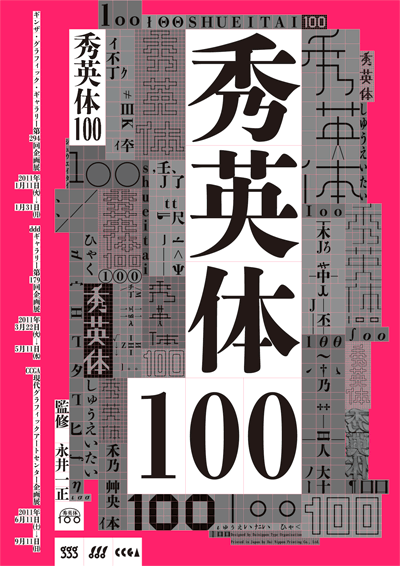
designed by Dainippon Type Organization
いまから100年前の明治末期、秀英舎が開発した活字は完成期を迎えていました。明治36年、43年、大正3年と立て続けに総合見本帖を発行しただけでなく、各活字サイズ・書体ごとの全字種見本帖も発行され、秀英体が量・質ともに充分だったことがうかがえます。
活版印刷からDTP用のフォント、あるいは電子書籍や映像で使われるなど、100年の間に秀英体も大きく変化してきました。そして2009年11月を皮切りに、モリサワから一般販売が開始され、より多くの方々の手に秀英体が届く環境が整ってきました。
今回の企画展では、秀英体生誕100年を記念し、DNPが創業当時から引き継いできた秀英体という文化資産の魅力を、より広く一般の皆様に親しんでいただくことがねらいです。
秀英体の四季
ギャラリーの1Fでは、24名+一組のグラフィックデザイナーによる「四季」をテーマに作成された新作ポスターを展示いたします。平成の大改刻で開発した秀英初号明朝、秀英明朝L/M/B、そして目下開発中の秀英角ゴシック&丸ゴシックを使ったポスターで、秀英体の新たな魅力をお伝えします。
©Kazumasa Nagai
秀英体の100年
地下の展示フロアでは、秀英体の誕生から平成の大改刻まで、秀英体の100年を書籍・雑誌・新聞広告・ポスター・電子書籍、さまざまなメディアや開発資料とともにご紹介いたします。
また、ワンパクによる、秀英体を使ったインタラクティブコンテンツも登場します。
ベントン母型のための原字
秀英体のリニューアルプロジェクト「平成の大改刻」、製作メンバーで、これまでの山あり谷ありを中間報告。また、開発資料がたくさんつまった秀英体展示室もご見学いただけます。
大日本タイポ組合のふたりが毎回ゲストを呼んで、タイポグラフィの面白さや発見などをゆるりと語り合う時間「文字Talk」の第3回目。テーマは「秀英体」。100年の歴史と、今後の発展について一時間にギュッとまとめてお話しします。
ジュンク堂書店池袋本店にて、秀英体が装幀に使われた書籍約20点のフェアを開催。期間中には、デザイナーの祖父江慎さんと一緒に、秀英体について、そして装幀における書体について、お話しをします。